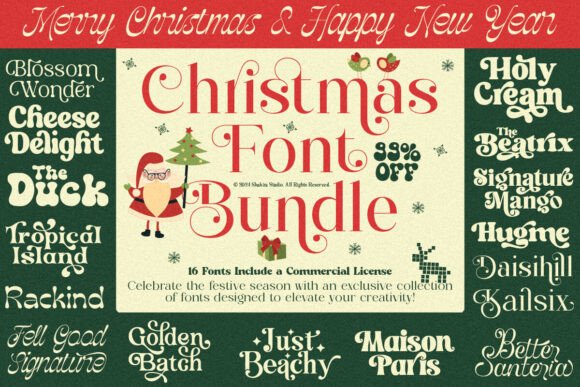
Christmas Bundle | Festive Holiday
Mencari elemen desain yang tepat bisa jadi sulit, namun Christmas Bundle | Festive Holiday menawarkan koleksi luar biasa yang akan langsung meningkatkan kualitas karya Anda.
Dibuat dengan presisi, Christmas Bundle | Festive Holiday menyediakan vektor yang bersih, tipografi yang halus, serta lisensi komersial untuk ketenangan pikiran Anda.
Baik Anda membuat produk POD (Print on Demand), undangan pernikahan, atau grafis media sosial, Christmas Bundle | Festive Holiday adalah pilihan yang sangat ideal.